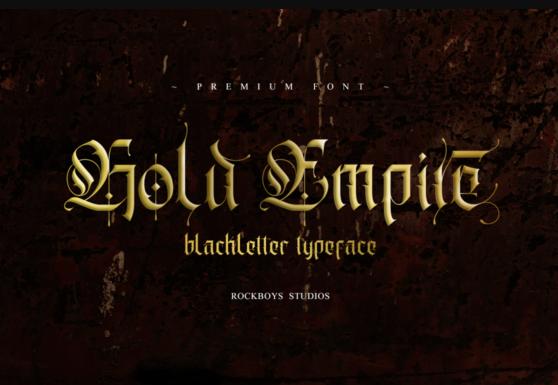
Gold Empire - это очень детализированный и элегантный шрифт с черными буквами. Смело добавляйте его в свои любимые творения и позвольте себе поразиться полученному результату.